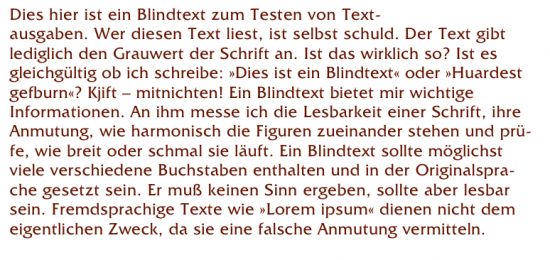
Schrift für Zivistellenbewerbung?
ich suche eine Schrift für eine Zivildienststellenbewerbung und wollte fragen, ob Ihr vielleicht noch Ideen habt.
Die Schrift sollte klar und gut lesbar sein, dabei jedoch etwas modern anmuten. Ob mit Serifen oder ohne ist ersteinmal egal.
Ich bin gerade halb am verzweifeln, da jede Schriftart, die ich mir angeschaut habe entweder zu nüchtern oder zu verspielt ist. Ein guter Mittelweg wäre das Optimum.
welche schriften hast du angeschaut?
kannst du geld ausgeben?
kennst du die neuen windows vista fonts beispielsweise die calibri?
Das Optimum für Unentschlossene: Optima
Im Übrigen sind die meisten Dienststellen schon froh, wenn es mal nicht Times New Roman, Arial oder Comic Sans ist. Wie wäre es also mit der Friz Quadrata
… wenn dieser Kalauer auf eigene Kosten genehm ist,
Ich habe mich jetzt für die Friz Quadrata entschieden.
Vielleicht doch lieber die Hobo…
Für den eigenen Bedarf hätte ich vermutlich die Charter genommen, robuste Schrift für einfache Bürokommunikation, aus dem Zeitungsumfeld. Muss ja nicht immer Times sein. Andererseits sieht die Friz Quadrata in 10pt gar nicht mehr soo bescheuert aus (hier in 12pt für den Bildschirm):575_friz_1.jpg
Es reicht mir zur Zeit, dass es keine standart Schrift wie Arial oder Times ist.